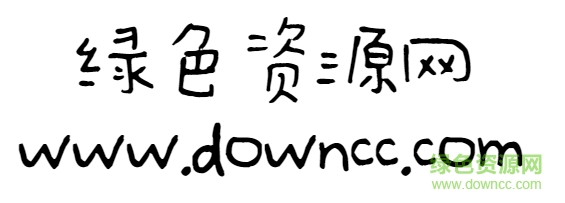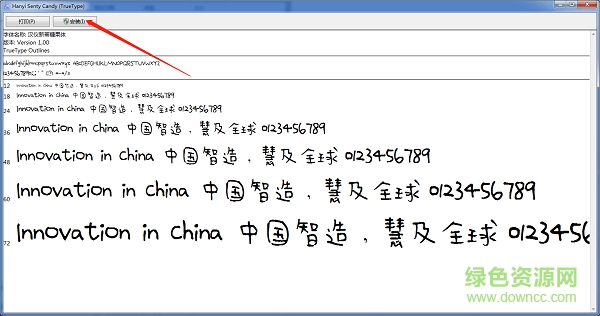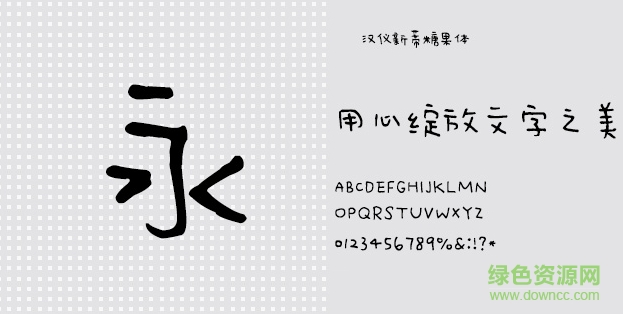
漢儀新蒂糖果體字體是一款看起來比較懶散的字體,字體簡約優(yōu)雅,筆鋒圓潤,非常適用于簡單的文章書寫排版,類似于手寫字,看起來舒適優(yōu)雅,喜歡的用戶快來綠色資源網(wǎng)下載吧!
漢儀新蒂糖果體是漢儀字庫開發(fā)的一款手寫字體,該字體配合精心編排的色彩搭配,每個字都負載著慢慢的可愛能量,就像糖果一樣,類似于小孩子書寫的字體,隨時隨刻給你帶來好心情!